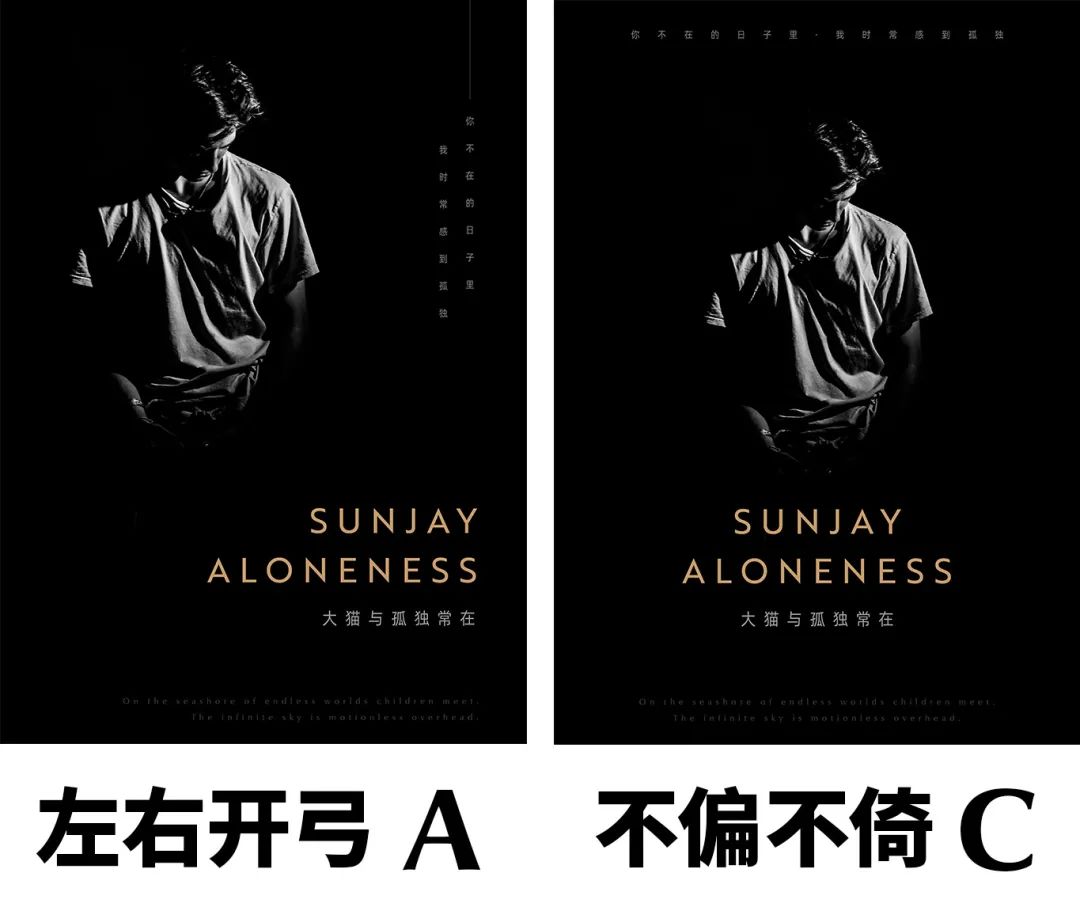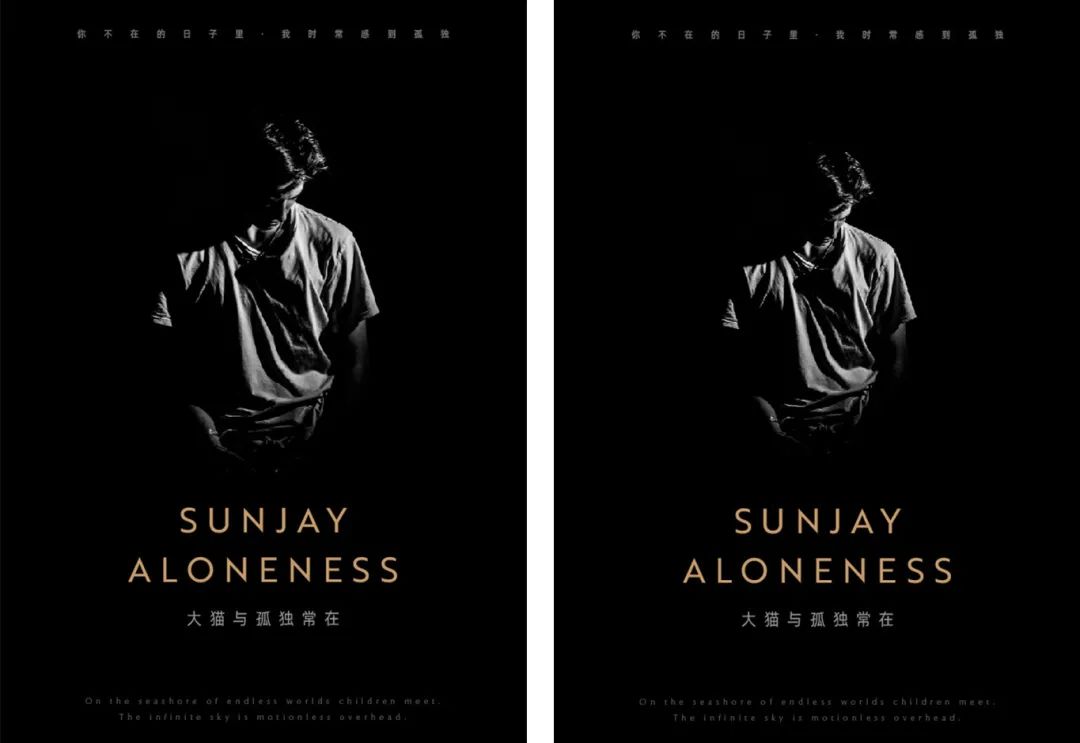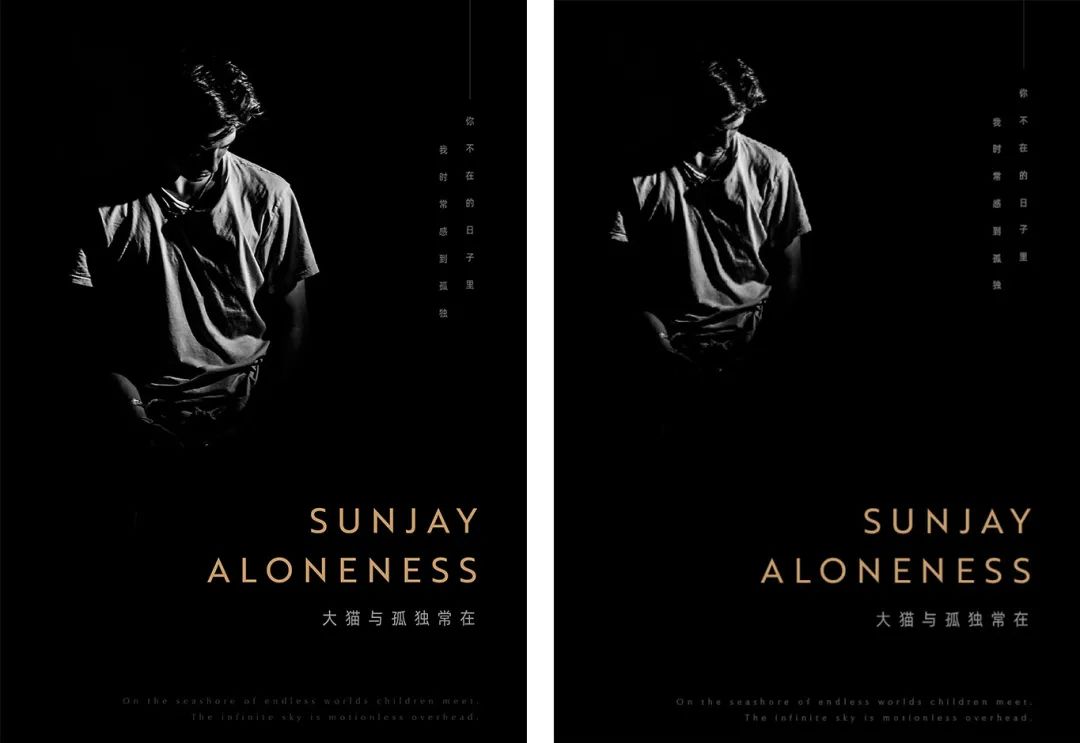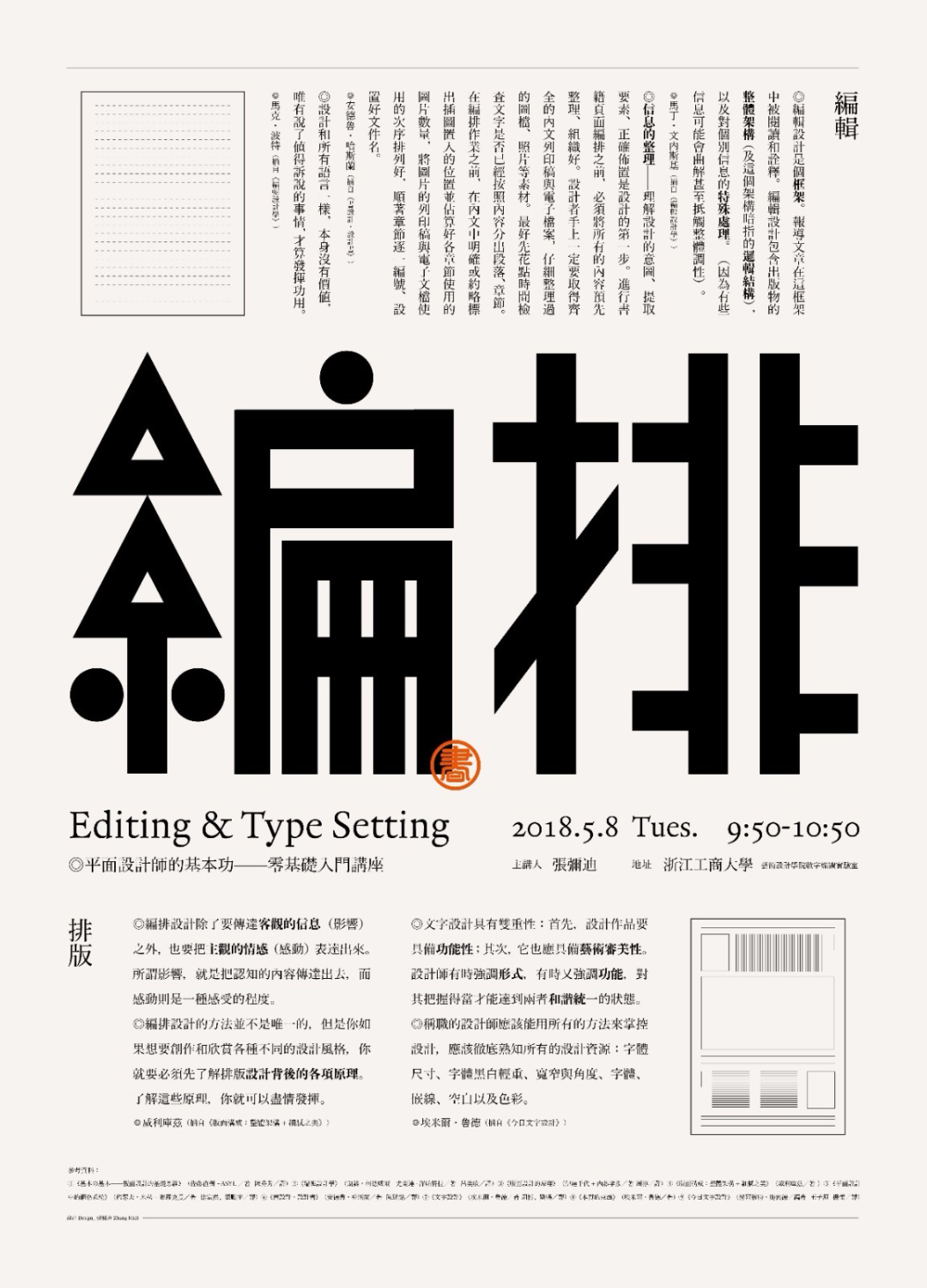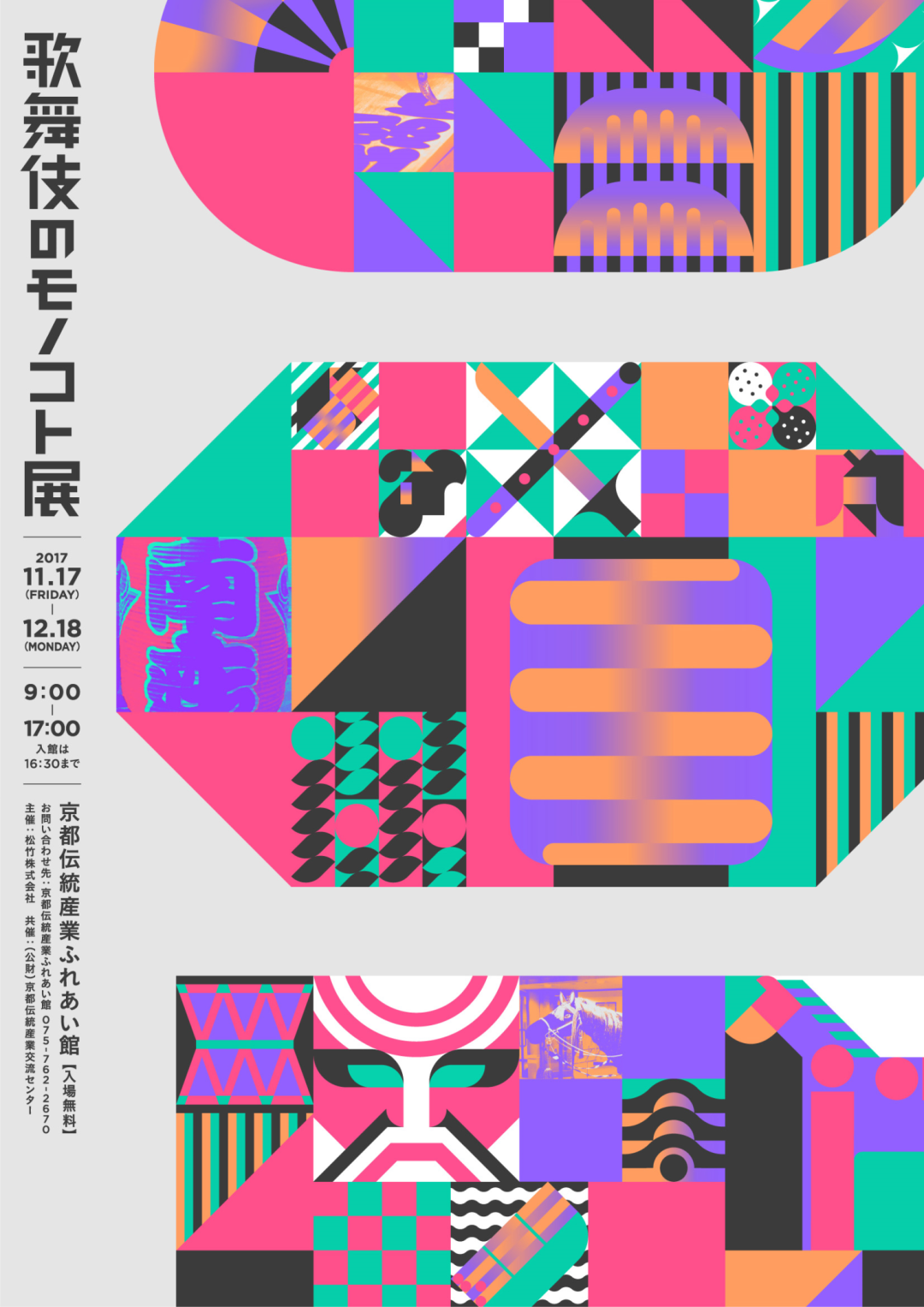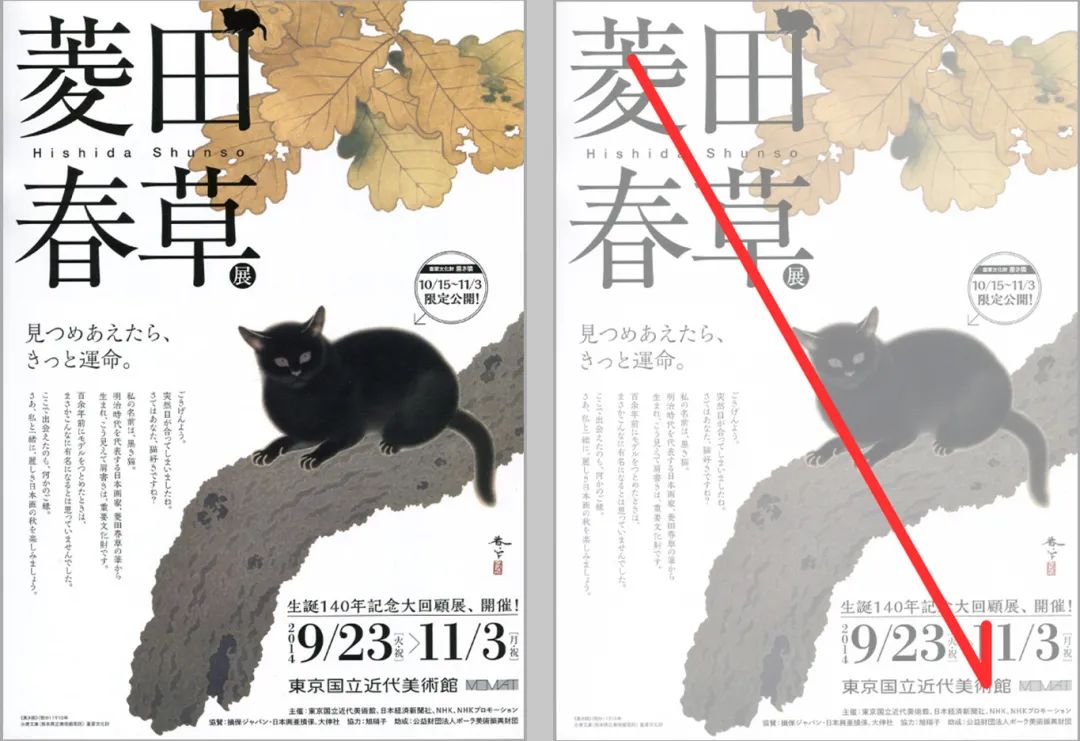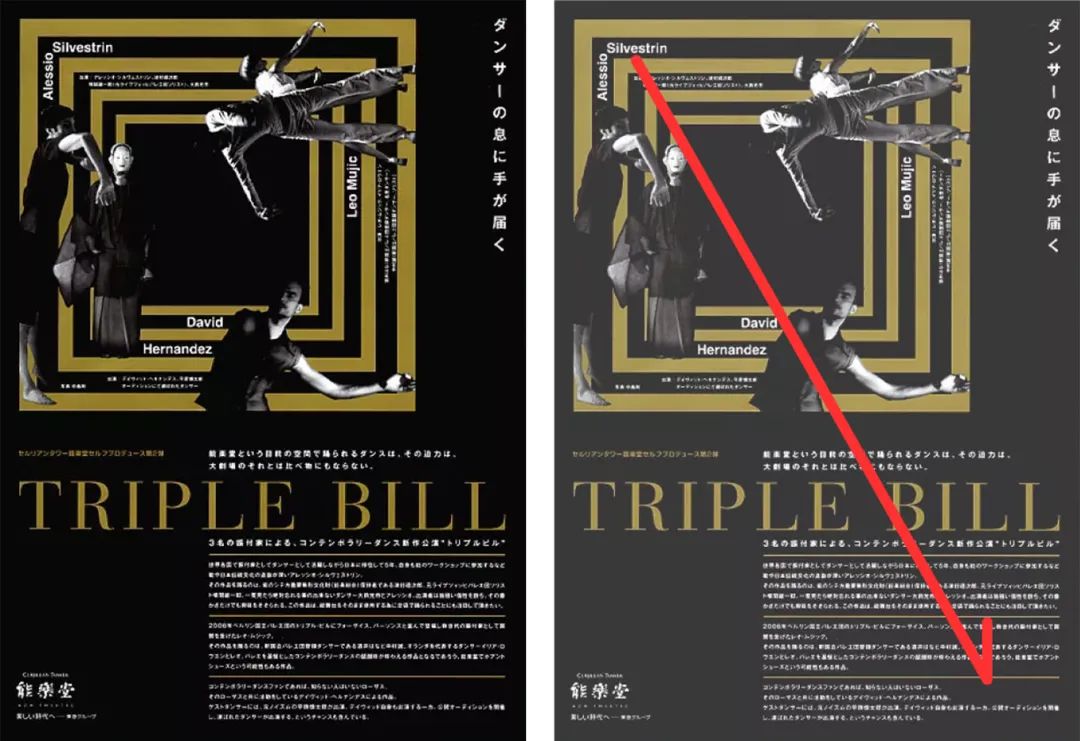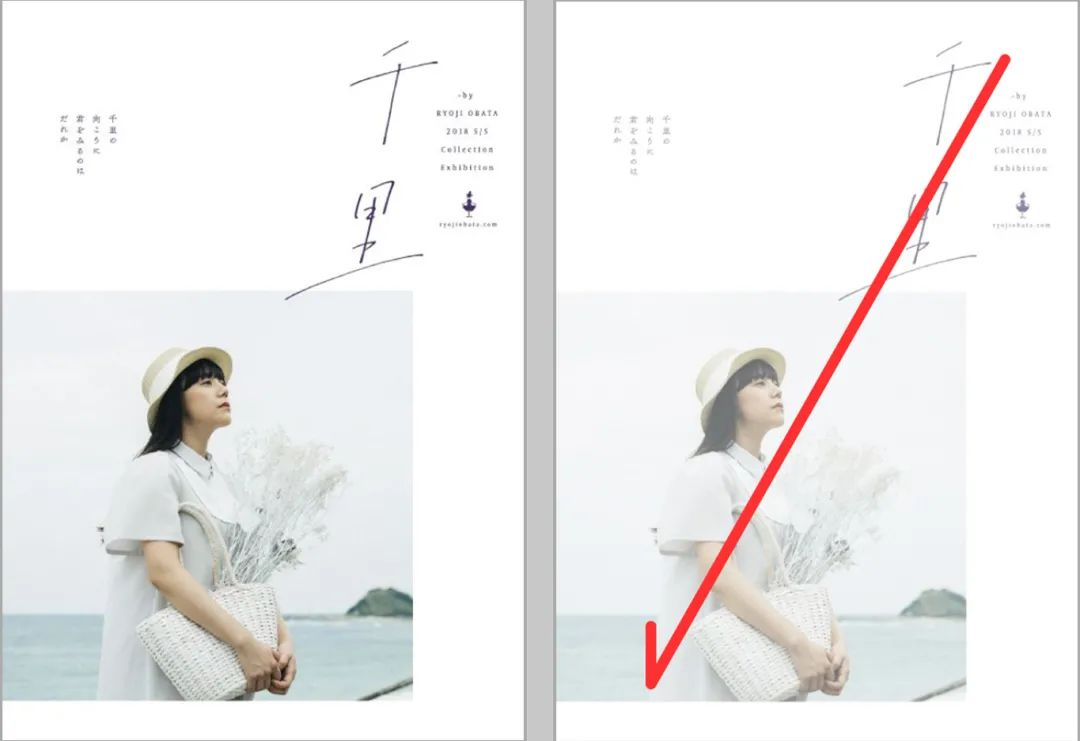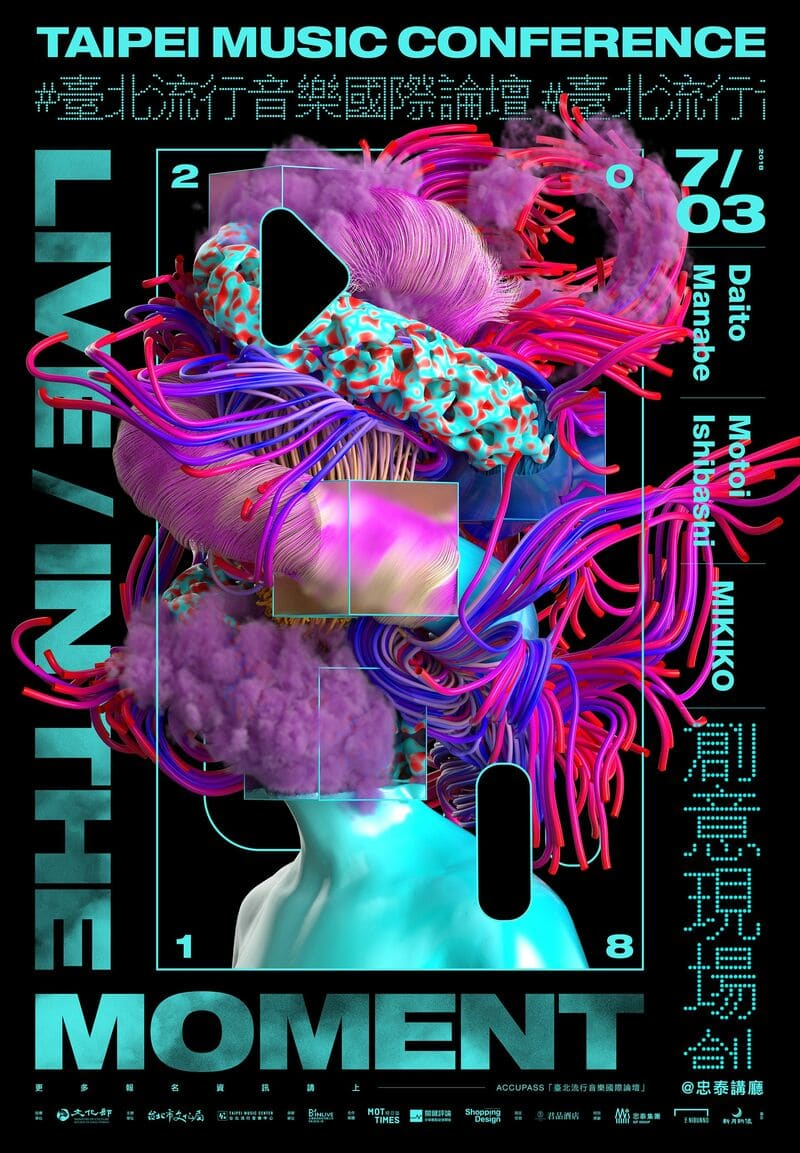
排版《玉女心经》之构图大法!
闲话少说,今个儿
咱们传授排版神功的「构图大法」,
跟着朕,一起疯狂吧!
「构图」为撒子要放到《玉女心经》的最后来讲?
当然是因为,
它远不如跳跃率、图版率等重要啦!
且「构图」灵活多变,
按照寡人理解,
每个版面,都可以延伸出多种构图!
具体可看文中《临江仙》的构图形式,
寡人可是花了几秒,每种构图都搞了一下~
不同构图虽有气质上的差异,
但对版面调性不会起到决定性影响~
咱先来瞧下问题~
下面俩版面,哪个更有正式、经典的感觉?
这必须是「不偏不倚C」呀,
不偏又不倚,就是居中,刚好就合适呗!
居中构图作为最常规、最传统的构图形式,
具有雍容华贵,经典、正式又有格调的气质!
不得不说,这雍容华贵的气质跟本王颇为相似~
而「左右开弓A」是对角线构图,
设计感确实比居中构图强,
毕竟居中构图太常规啦,就是一老古董。
对角线构图有了变化,也就有了设计感~
但是吧,
设计感强了,正式和经典的感觉就弱啦!
简直是,鱼与熊掌不可兼得也~
虽然鱼与熊掌不可兼得,
但天下与美人可皆归寡人呀~
众爱卿若不想让朕独享,
那就让朕考考你们~
在构图之前,
咱们说了「图版率、跳跃率、留白、字体」等几大块,
他们与版面的气质息息相关~
上面两个虽然构图不同,
但图版率、留白等都是差不多的。
所以除了经典、正式的感觉不同,
两者都能够传达高端、昂贵的感觉~
那么,如果他们构图不变,
又想让他更高端、更精致,
咱可以怎么做?
A.增加图版率,缩小留白
B.减小图版率,增加留白
若众爱卿已习得前几篇功法,
自然是知道这题选「A」!
留白大了,
精致、高端、格调感就更强了!
答错的童鞋,
罚你们加练是遍前几套心法~
只看文字,还有爱卿不信,
那本猫只好使出闪电五连鞭,快速改改了!
啪的一下,很快就改好了~
其他地方没动,仅仅是把人物缩小了。
居中构图也是一样滴,
只是把留白放大,
给人的感觉就更精致、高端~
如果这是奢饰品海报的话,
这么一改就让寡人更买不起了~
o(︶︿︶)o 唉,
贫穷使我们相遇,说多了都是泪~
通过这个小案例,
知道寡人为啥把构图排在最后了吧!
因为确实木有其他几个要素重要呀~
通过前几篇功法的要素,
拿捏准了气质,
再用构图锦上添花才是正道。
寡人一般把常见的构图形式,
归类为8种,
接下来跟着朕的脚步,
在寡人挥动的皮鞭下,
一起来看看吧!
01.分割式构图
猫说:
不把身心全部给我,
就让它一刀两断!
分割式构图,
就是一刀下去把版面斩成两段,
亦或是三段~
简而言之,这种构图形式,
就是把版面,水平或垂直的分割,
一般包括 上下、上中下、左右 的构图结构~
只说肯定不懂,
且看老夫2秒钟排的示范图就晓得啦!
(寡人就是快!)
上下结构
上下结构也就是把版面分成上下两块,
具体布局可以是上图下字,或者上字下图。
PS:
「上图下字」中的「图」,不单指图片哟!也可指代较大的标题或元素~
这种布局结构最常规,也就最不容易出错~
正如练此功,最不容易纵火入魔一样~
咱再来看一下上下结构的例子~
美术馆展览的这张海报,
便是上文下图的结构~
这种编排形式,很难出错,
当然也很难出彩啦~
猫说:
凡事皆相对,
得到一粒沙子,
亦会失去一粒尘埃。
这个海报是上图下文的结构,但却非常活泼~
这是因为,下方信息编排很个性,
跳跃的文字和曲线的加入,
使这块异常活泼~
上中下结构
上中下结构,就是把版面分成上中下三部分,
相当于上下结构中间又插了一道信息区~
简而言之,
就是从上下两块信息区,
变成了上中下三块信息区~
这张海报便采用了上中下的结构,
标题放于中间信息区,
上下则为详细阅读的文字~
也可以变成上下是图,
中间是文字信息的结构~
左右结构
同上,也就是把版面分成左右两部分,
左图右字,或者左字右图。
左右结构也是比较常见的一种构图。
这个海报左侧是主标题,右侧是详细信息~
当然是非常正点的左右结构啦!
留白也是面积哟!
这个海报,左边是图,
右边大面积的留白中加入文字,
当然也是左右结构啦!
海报文字信息居于左侧,
虽然文字只占很小的一块,
右侧大部分是插图。
但依然不妨碍它是左文右图的左右结构~
02.居中式构图
居中式构图,
也就是版面整体布局以居中对齐为主,
左右两侧基本对称的结构。
对称式的布局结构,也属于居中式构图的一种~
居中式构图传达的感觉比较经典、正式。
这个气质,相信众爱卿在开篇的小案例中已经领悟啦~
居中构图,确实会有这么个经典、传统、高端的气质在里面~
也正因为此,很多电影海报都采用居中式构图。
虽然居中式构图具有传统、经典感觉,
但这个也不是绝对的,
一切还要看其他几个要素的设定,
比如下面这个音乐会的海报~
虽然是居中式,左右对称的结构,
但是却有一点活泼感~
这是因为他的字体非常有张力,
版面率大,而留白又小造成的。
所以呀所以,
构图虽重要,
但却排在前几套功法之后~
03.对角式构图
开篇案例中,咱也说过了对角式构图~
对角构图,
画面主要元素一般分布于对角,
视觉流向是倾斜的。
相对于居中构图的形式,
对角式构图增加了不稳定的变化,
毕竟视觉流向从垂直,
变成了斜线~
所以具独具一格的感觉~
这个海报,标题与右下方图案形成对角构图~
这个则是从左上到右下的对角~
这个比较具有艺术感的海报,对角从左上到右下~
我们可以看到,
对角式构图的设计感,
比居中式的强很多。
这也是因为,他更具有变化!
04.四角式构图
上面的对角,是元素压住两个角,
但今儿个,寡人把另外两角也没收啦!
压住四角式的构图形式,
就是四角式构图~
当然,你叫他压角式构图也可以。
一般来讲,四角式构图主要是
用字把主体四角或版面四角压住的形式~
这种构图方式比较稳定,
传达的气质在活泼与安静之间~
四角式构图给人感觉四平八稳,
这种形式一般标题比较大,
所以亲和力还是挺强的。
废话~能压住四角的字,当然要大啦!
更具体气质
结合其他几个要素综合来看啦~
像这个鹤的海报,主体表现力很强。
虽然是压角式构图,
但正文/LOGO部分在整个版面,
是居中对齐的~
所以海报既有冲击力,
又带有一点居中构图所有的典雅气质~
05.包围式构图
是谁?
在朕的寝宫四周竖了高墙!
是要把朕关在寝宫不成?
包围式构图,
正如上面缩写~
此种构图,
一般图片或主体四周布满文字。
若把主体比作寝宫,
文字比作高墙,
那可不就是把朕囚禁在寝宫嘛!
包围式构图形式比较饱满,
信息也比较多,
毕竟版面率比较大,
所以一般还是挺活跃的。
除此之外,风格气质取决于主体的内容~
上文中这个压角式构图的案例,
其实也算是包围式的构图,
毕竟他的城墙把寝宫堵住咯~
包围式构图因为信息量比较多,
版面率高,留白少,
自然显得比较热情,且有活力啦!
这个包围式构图虽然留白大一点,
但四周的文字决定了版面率的大小,
因为版面率较大,
所以也是比较活泼的~
这个包围式构图就非常活泼了。
因为除了版面率大,
更重要的是主体表现力高,有冲击力!
06.曲线式构图
画面主要元素成「S形、Z形、C形」等,
总之,
版面主要元素走向,
非常妖娆就对啦!
曲线式构图,相对于对角式构图来说,
更不稳定,更活泼!
自然就更具有设计感啦!
虽然更活泼,更易做出设计感。
但若用不好,
就会出现阅读逻辑混乱的情况,
所以众爱卿,
用此邪功,
必得先定好阅读逻辑,
再依照轻重缓急去安排版面哟!
这个海报以打开的书和文字,
构成一个反S的构图。
以标题和线条插画,
构成S形构图。
这是王志弘做的《你是人间四月天》的书封,
「四月天」放大构成一个C形。
我们可以看到,
曲线构图通过元素间的位置关系,
会引导我们视觉流向变成曲线,
所以也是比较有设计感的构图形式~
07.散点式构图
这个嘛,
说白了就是,
把文字或其他小元素拆散成点,
再布满版面的形式。
这种构图看上去非常活泼,
又具有设计感,
简直是旋转、跳跃,我睁着眼~
那份活泼,在我心间呀!
为啥这种构图看上去十分活泼嘞?
当然也是因为这种形式,
使版面细碎,留白不能形成整体,
留白就显得少,版面率自然就更大,
那必须就活泼、跳跃鸭!
08.轴线式构图
画面中有一条隐藏的轴线,
大部分元素都沿着轴线对齐,
这便是轴线式构图啦!
So,Easy!
看到画面中有条很浅的竖线了咩,
这个就是这个版面的轴线~
YANG SHEN 和正文,
都是靠着这条线对齐的。
一家人嘛,就要整整齐齐,
这条线就是家规咯~
看到这个图,众爱卿心里一阵嘀咕,
这厮不是对角式构图里的案例嘛,
啷个又在这里出现了?
难道猫皇老迈年高,
已经记忆模糊了不成~
但实际上,专辑上的文字并不是绝对居中的
红色的线是中心线,
为啥文字没有居中对齐,就差那么一丢丢嘞?
因为,
文字的编排要与图片和谐搭配,
专辑图片是十字形构图形式,
沙发为横轴,人物的眼睛与手指方向连成纵轴。
文字根据纵轴走向排列,
使手眼和文字,连成了整体,
那必须就完成了生命的大和谐!
除此之外,
下方「周杰伦」和「Jay」的编排形式,
也是一个十字轴哟!
字体也设计的非常Nice!
好啦,到此,
常见的8种构图形式,
算是讲完啦。
最后咱再总结一下~
当然,除了这8种,
还有 几何构图、放射式构图等,
但这些用的并不多,
而且大多数也可以概括为这8种,
寡人就暂且留着,
日后有机会再讲~
不知不觉又 4000 字啦,
本来还想再写点,
根据主题造型确定构图形式,
如今只好留到下一篇咯~